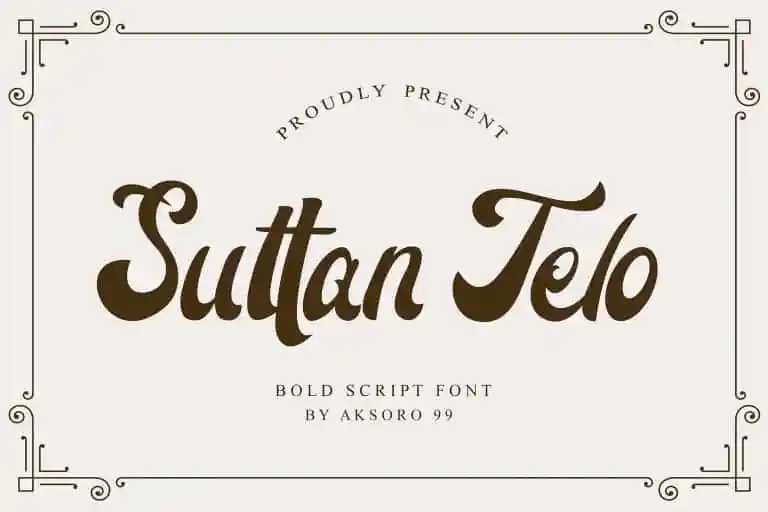
Suttan Telo Script Font – Download Grátis
A Suttan Telo Script Font é uma escolha perfeita para quem busca um estilo moderno, elegante e sofisticado no design editorial. Criada pelo designer Aksoro 99 Nugroho na plataforma 99designs, essa fonte está disponível em versões bold e retro. Ela oferece letras afiadas e belas que criam uma aparência moderna, tendinosa e elegante. Este estilo de escrita é ideal para aplicação em diversas áreas do design gráfico, desde a criação de logotipos até o design de moda e publicidade. A Suttan Telo Script Font se adapta perfeitamente às necessidades de ambientes como estampas de roupas, panfletos e revistas, oferecendo um toque sofisticado sem comprometer a funcionalidade do texto. Seja para uma campanha publicitária ou uma página web de estilo minimalista, essa fonte atinge o ponto preciso entre a modernidade e o encanto tradicional.